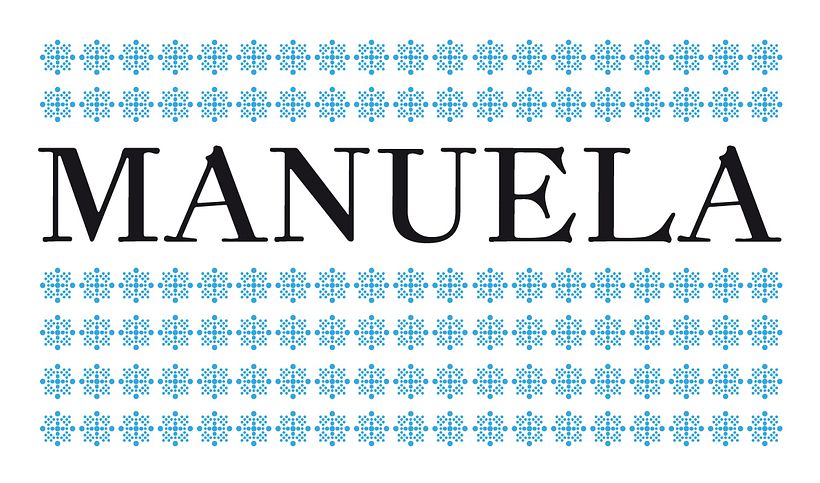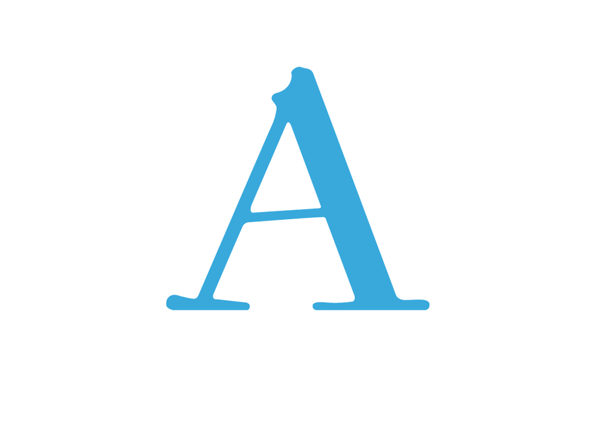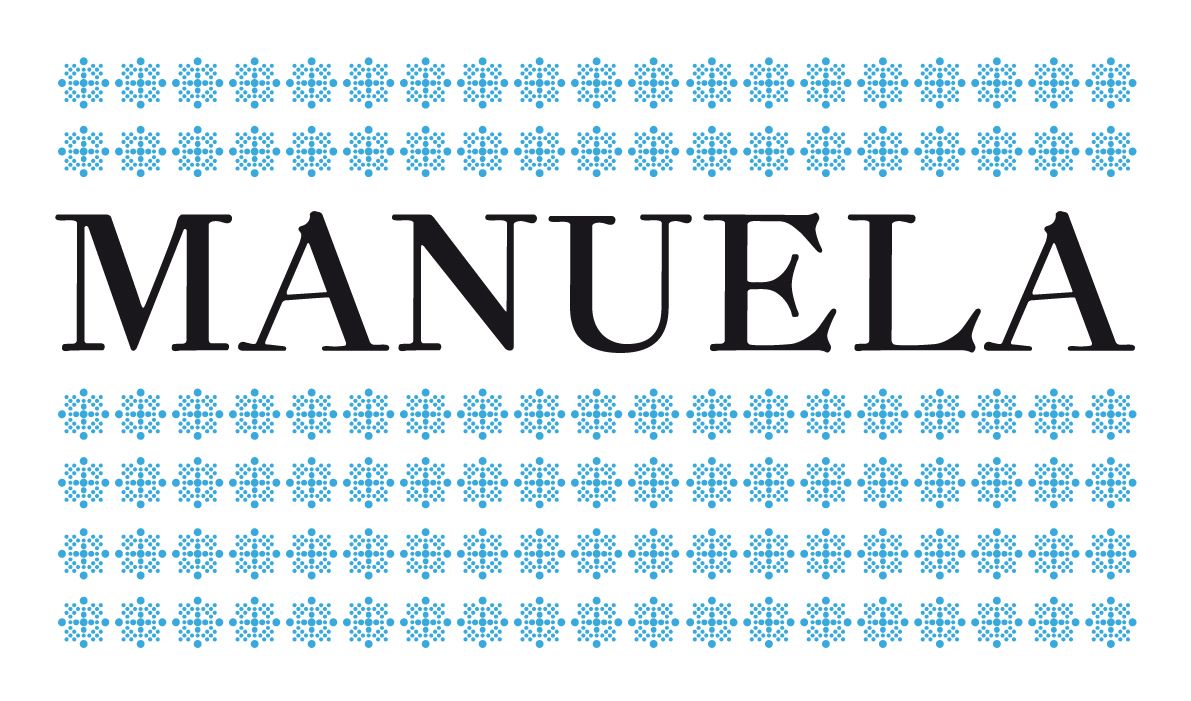
Manuela typeface
Typography based on the prints made in the 18th century by Manuela Contera, widow of Joaquín Ibarra. In 1805, the probable date of her death, the business passed into the hands of her daughter, beginning a decline until it was sold and dissolved in 1836.
Tipografía basada en las impresiones realizadas en el siglo XVIII por Manuela Contera, viuda de Joaquín Ibarra. En 1805, posible fecha de su muerte, el negocio pasará a manos de su hija, iniciándose el declive hasta su venta y desaparición en 1836.